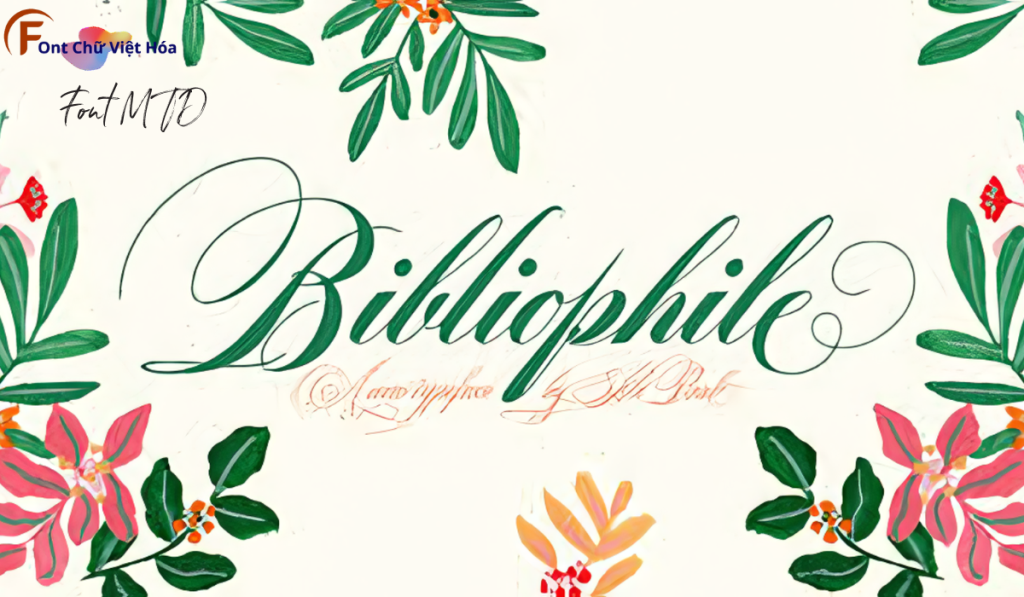
Font MTD Bibliophile Script Việt Hóa
Phân loại: Cá tính, độc đáo
Kiểu chữ: Có chân
Font MTD Bibliophile Script Việt Hóa, thuộc bộ font MTD, mang phong cách viết tay mềm mại và tinh tế, lý tưởng cho các dự án thiết kế như thiệp mời, bìa sách, và các sản phẩm thủ công. Với các nét chữ uyển chuyển và độ dày đều đặn, Font MTD Bibliophile Script Việt Hóa không chỉ dễ đọc mà còn tạo cảm giác nghệ thuật và thanh lịch. Việc Việt hóa font giúp người dùng dễ dàng tích hợp vào các thiết kế tiếng Việt, mang lại sự tiện lợi và nâng cao tính thẩm mỹ.